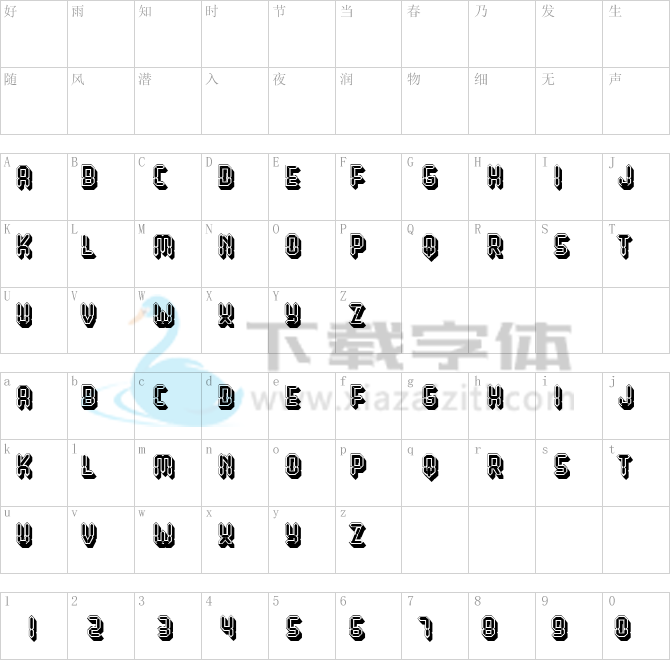
Affichage.ttf字体下载,这款字体结构工整、笔画清晰,兼顾美观与易读性,适用于标题、正文、海报、包装、LOGO 等多种场景。字形优雅稳定,风格百搭耐看,适配日常排版与创意设计,让文字呈现更舒适、更具质感。Affichage.ttf字体下载一笔一画,皆是细节,以均衡的比例、流畅的线条打造舒适视觉体验,字形端正大气,风格简约现代。无论是商业设计、品牌宣传还是日常排版,都能轻松驾驭,让文字更有格调与力量。Affichage.ttf字体下载字体下载。